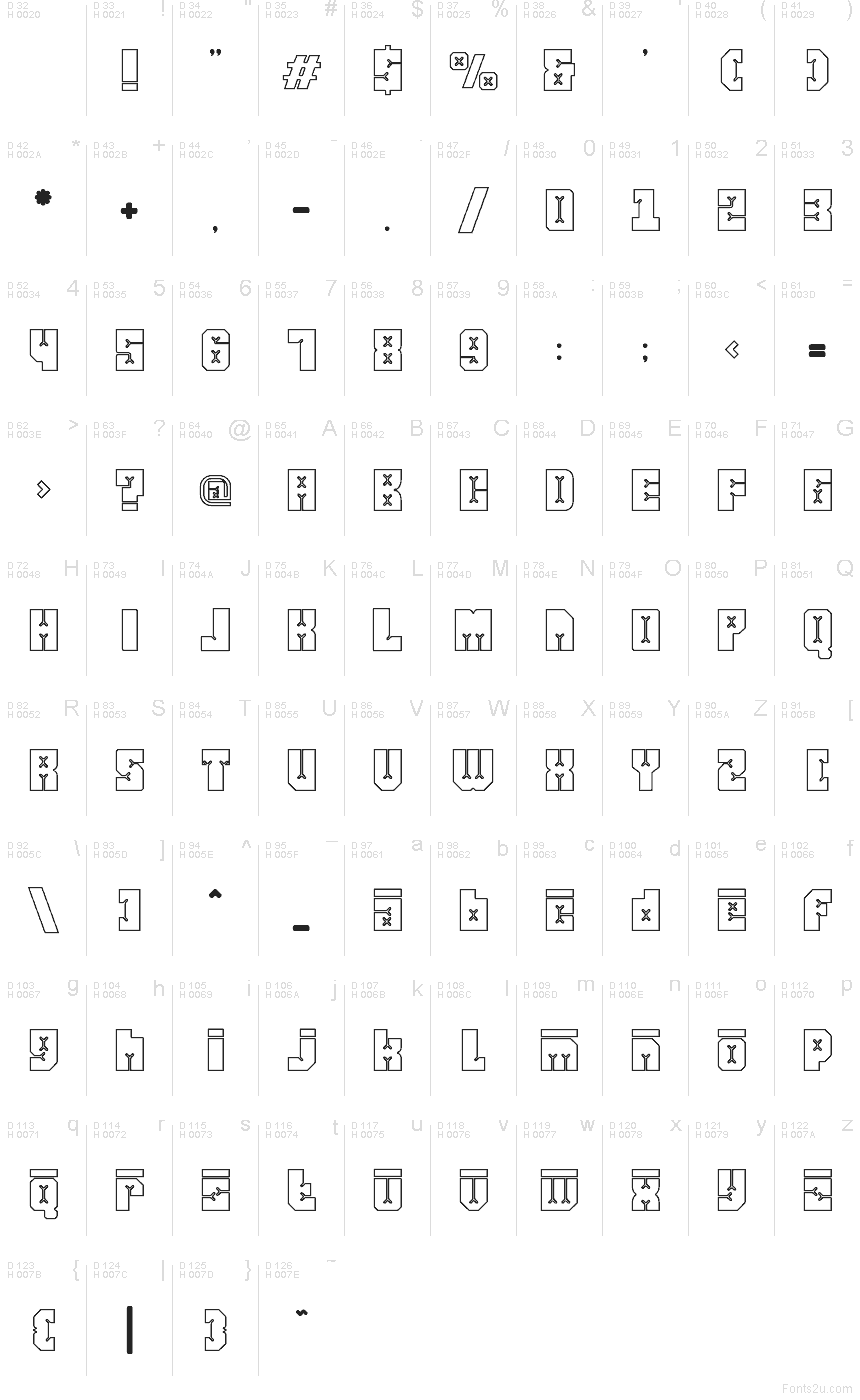
Friez Five
Friez Five od Putracetol Studio je bezplatné, obrysové groovy písmo typu display, definované vysokými blokovými tvarmi, vnútornými linkami a ostrými diagonálnymi zárezmi. Vďaka nim pôsobia znaky pevne, no nie stroho. Opakujúce sa vidlicovité prvky pripomínajúce vetvy narúšajú obdĺžnikové siluety a dodávajú dizajnu osobitý, rytmický nádych.
Kombinácia geometrickej štruktúry a drobných neobvyklých prvkov skvele vynikne v titulkoch na plagátoch, obaloch albumov, streetwearovej grafike, obaloch produktov či v nápisoch typu logo. Friez Five sa skvelo hodí aj na bannery na sociálne siete alebo letáky, kde vďaka obrysovej konštrukcii získavajú veľké slová grafickú úlohu, ktorá sa blíži skôr k nápisom než k bežnému textu.